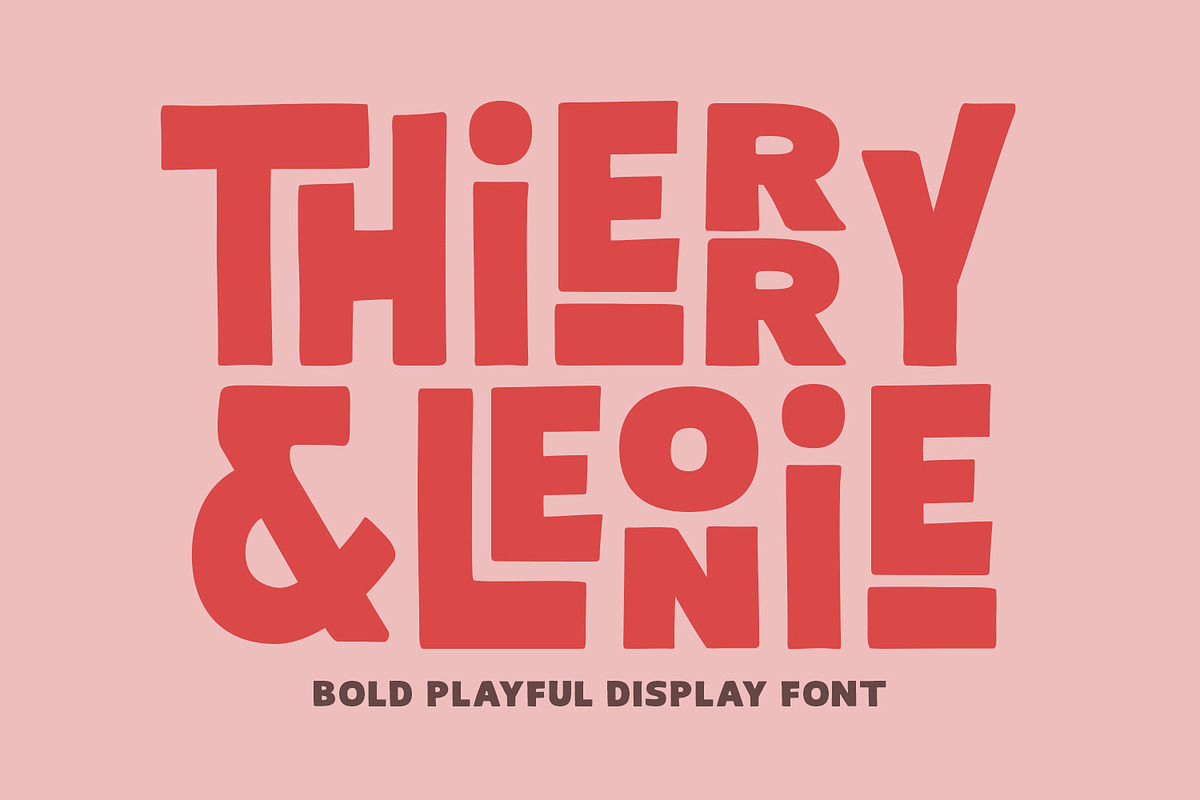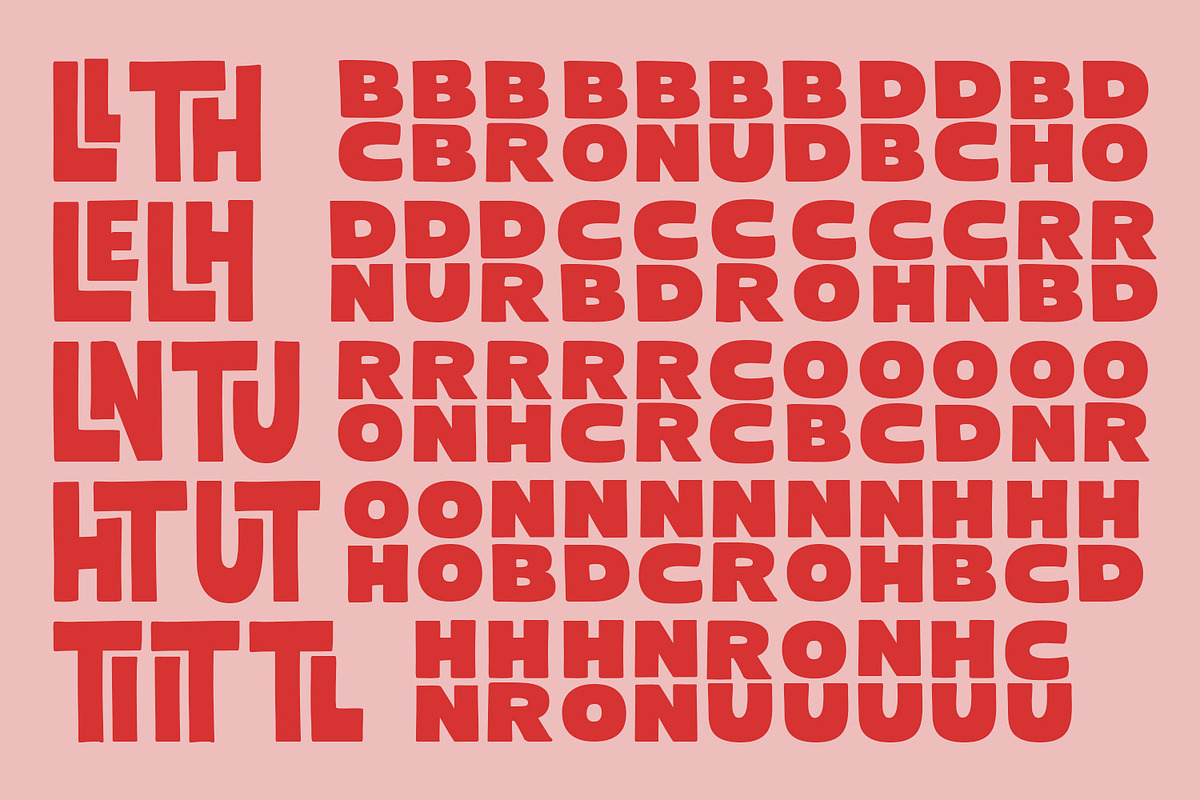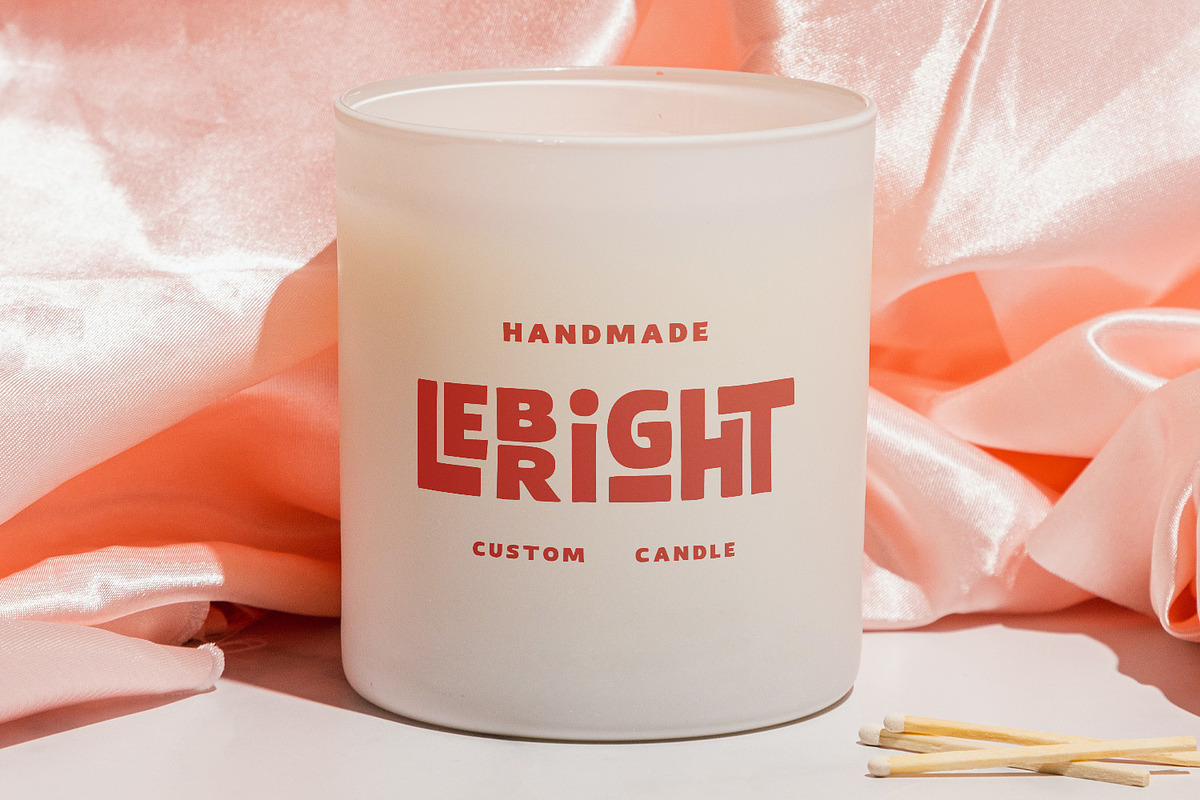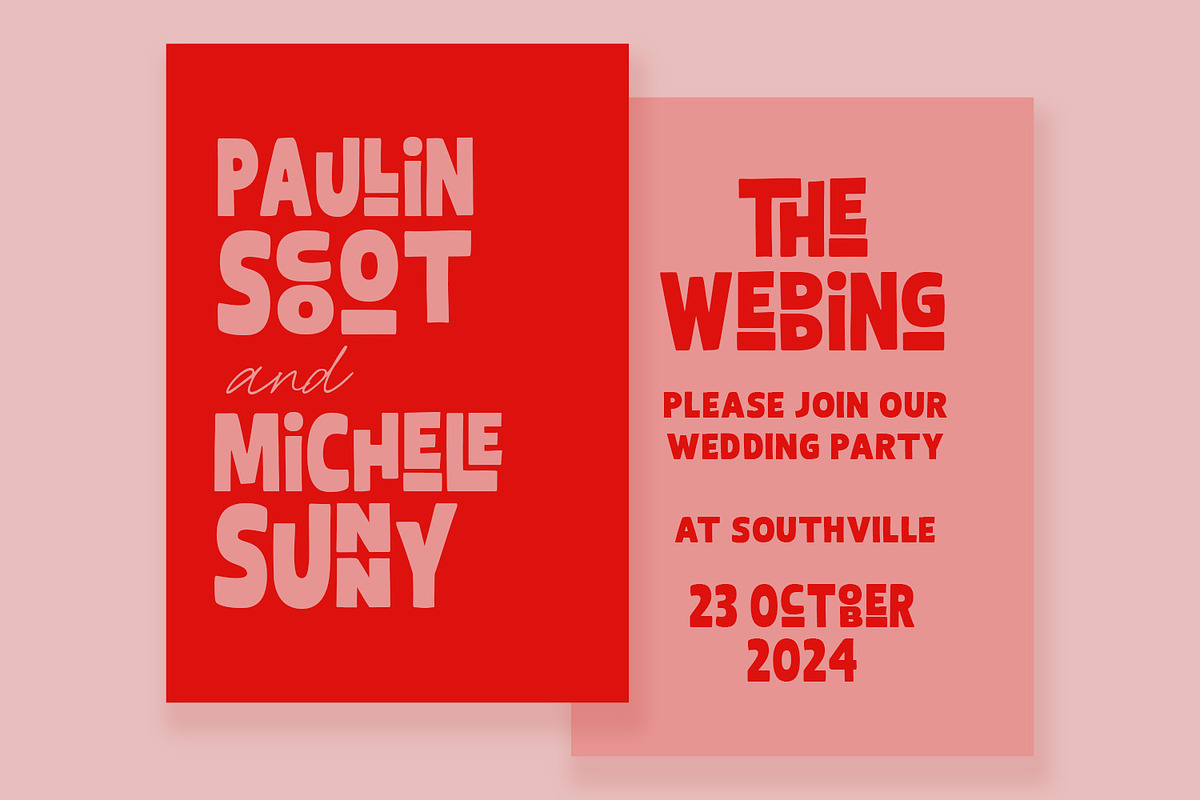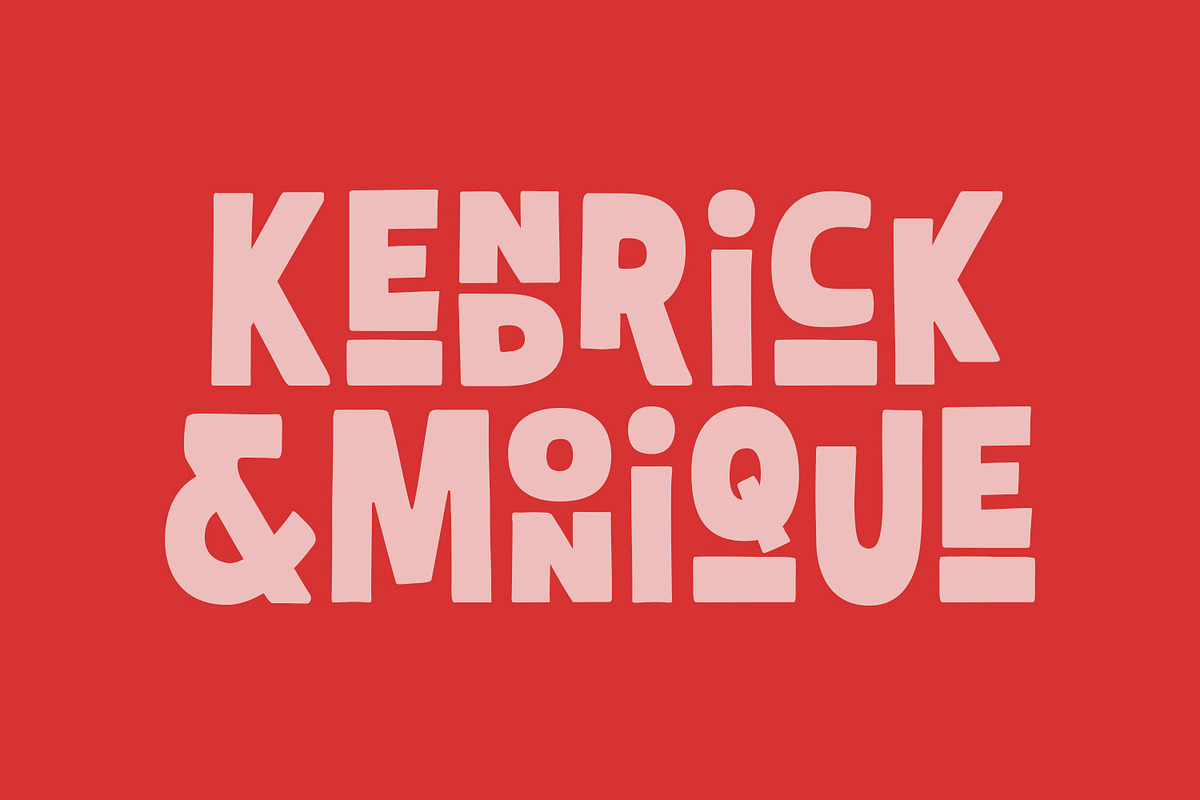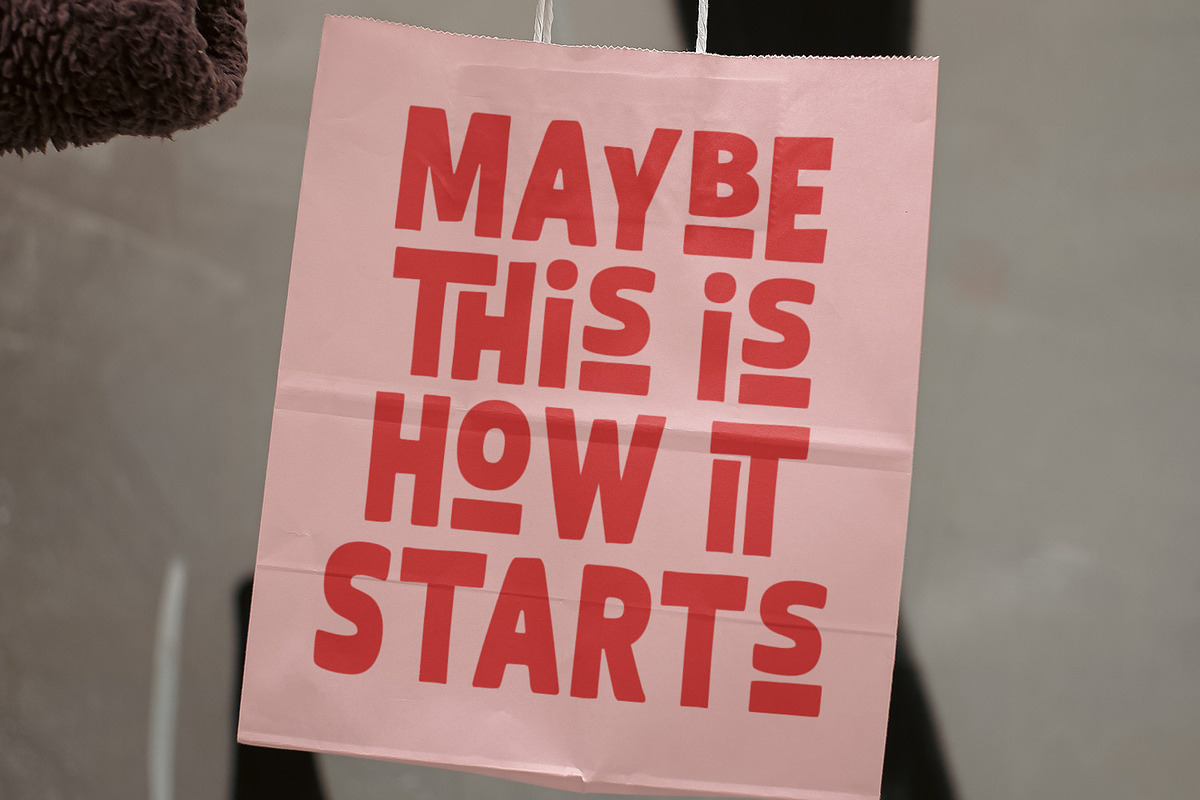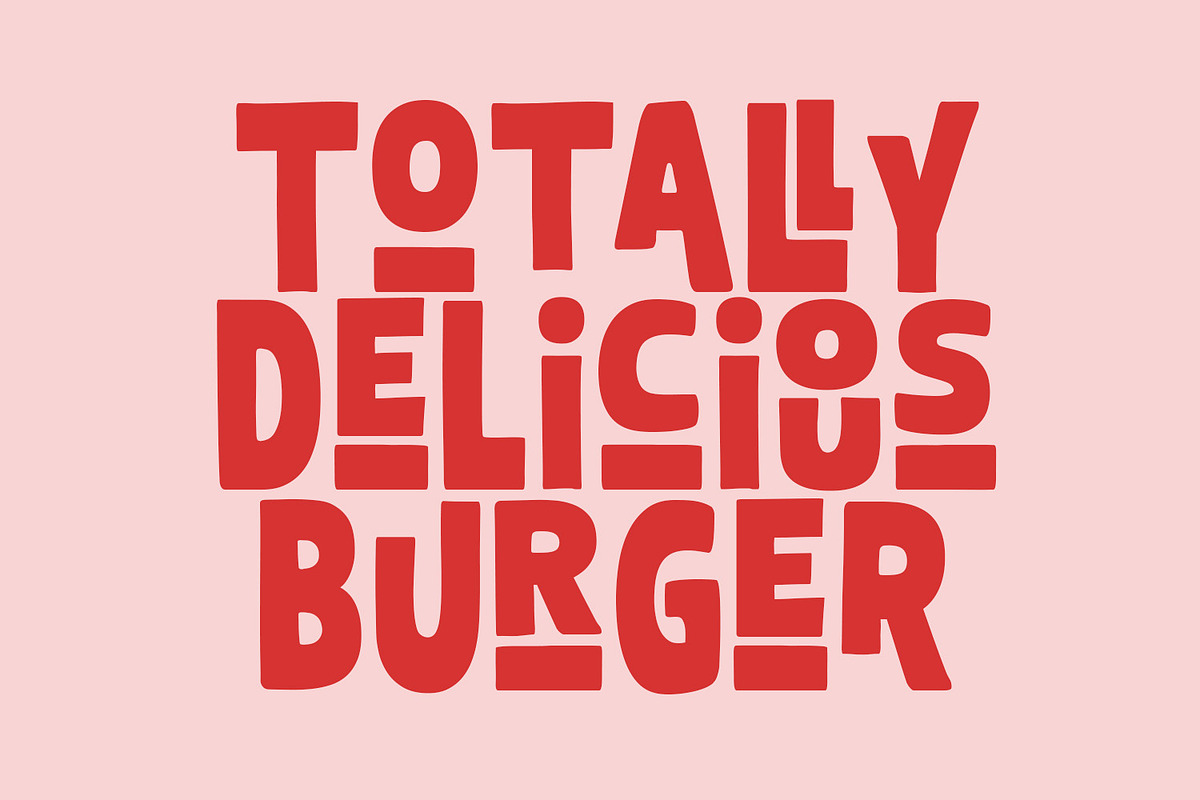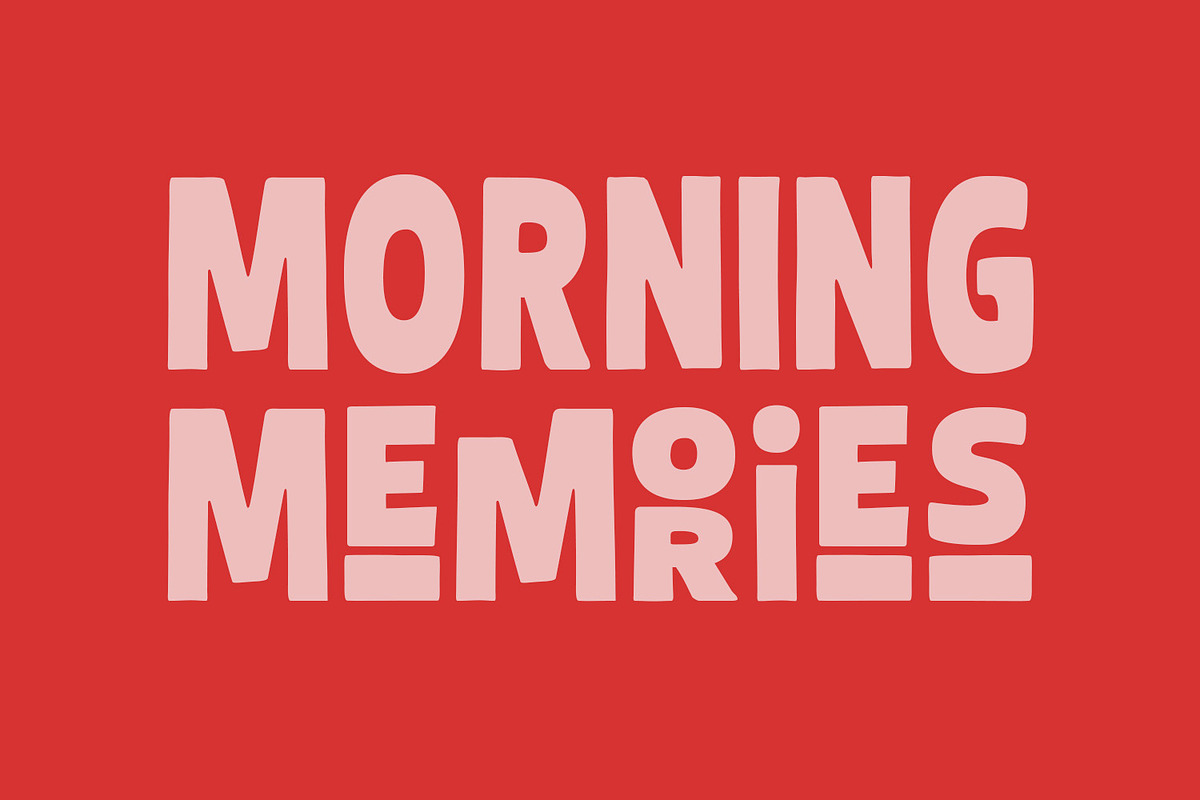
Thierry Leonie – Bold Playful Font
Thierry Leonie – Font Display Ceria & Bersahabat untuk Desain Penuh Karakter
Perkenalkan Thierry Leonie, sahabat baru Anda di dunia tipografi! Font display ini hadir dengan gaya kondensasi yang tebal dan penuh keceriaan, cocok untuk menambahkan sentuhan personal pada setiap proyek desain. Dengan desain sans-serif yang bersahabat dan kaya akan ligatur, Thierry Leonie terasa seperti pelukan hangat untuk setiap karya kreatif Anda.
Gunakan font ini untuk headline yang mengundang, logo yang unik, poster yang menyenangkan, atau berbagai proyek desain lainnya. Thierry Leonie bukan hanya tampil menawan, tapi juga fleksibel untuk berbagai gaya dan suasana.
Mengapa Thierry Leonie?
• Gaya sans-serif kondensasi yang unik dan ekspresif
• Ligatur kreatif untuk tampilan lebih menarik dan dinamis
• Cocok untuk branding, desain kemasan, media sosial, undangan, dan poster
✨ Biarkan kreativitas Anda bersinar dan rasakan kehangatan dari Thierry Leonie, font yang membawa keceriaan ke dalam setiap desain Anda!